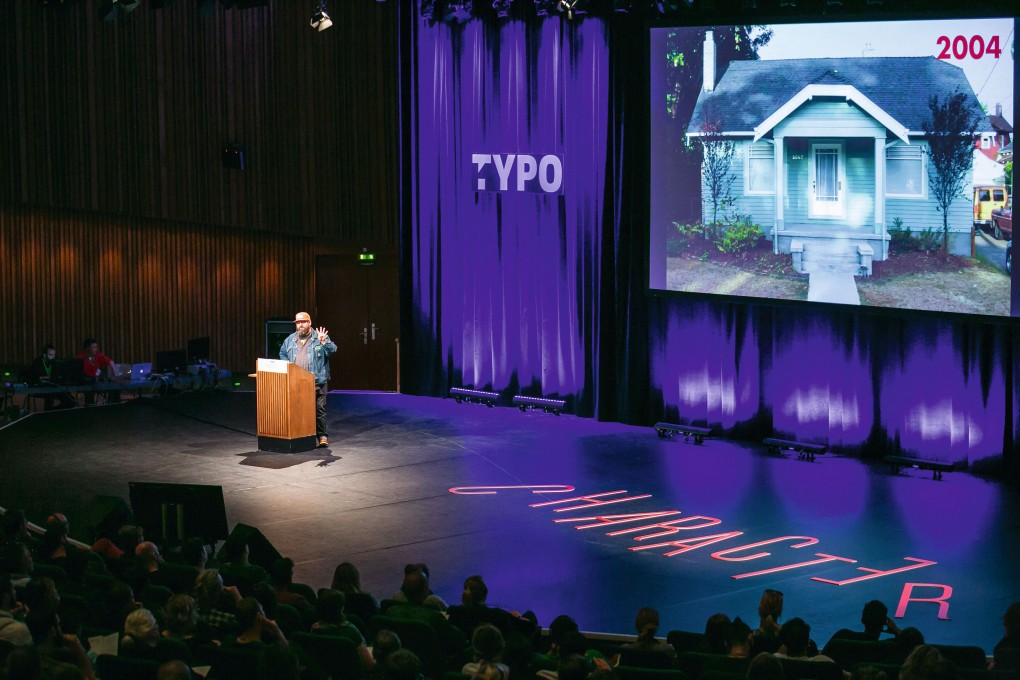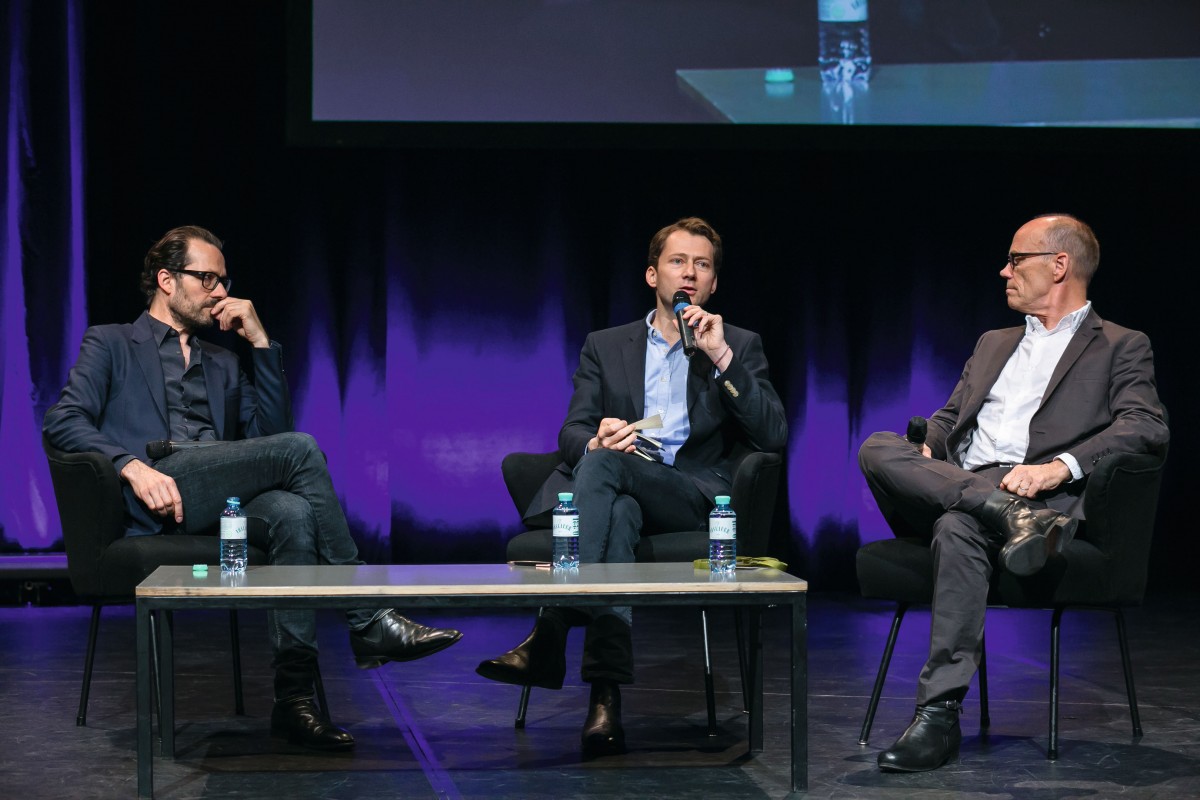
2015 타이포 베를린 : 3 days of Typo Berlin
베를린의 연례 타이포 컨퍼런스 ‘타이포 베를린’은 올해 세계문화의 집(Haus de Kulturen der Welt)에서 진행되었다. 디자인 연설자들의 정수에 해당하는 3일의 강연을 듣기 위해 다양한 분야의 창작자들이 먼 곳에서부터 이곳을 찾았다.
타이포 베를린 2015
Day.1
타이포의 첫 번째 연설자는 철학자이자 문화 이론가 존 소와(Jon Sowa)였다. 그는 현대 디자인 뒤에 숨겨진 전위적인 가치관에 관한 깊은 탐구를 하며 참가자들과의 대화에 불을 붙였다. 사회 세계를 해방적인 방향으로 발전시키려는 움직임과 세계 자본주의에 적응하라고 강요하는 시장 사이 이어지는 갈등에 대해서도 이야기했다. 소와는 창작자들에게 이를 ‘현대 예술적인 창작물의 가장 중요한 특징’으로 인정하길 촉구했다.
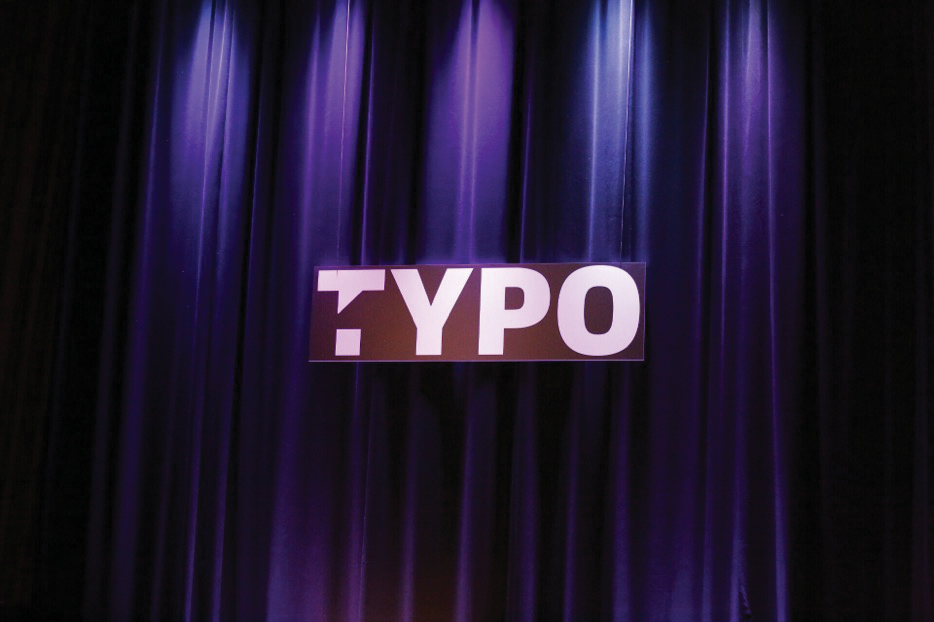
Typo 2015, Berlin
사람들을 휩쓸고 간 이 개관은 프랑스의 장 프랑수아 포르셰(Jean Francois Porchez)의 이야기로 이어졌다. 서체의 개성과, 디자인은 ‘생각의 시각화’라는 조금은 더 미묘한 주제의 강연이었다. 포르셰는 동시에 이러한 이야기도 했다. “좋은 디자인은 보이지 않는 디자인이다. 눈에 보이지 않는 것을 어떻게 만들어야 하나?” 그는 자신이 파리의 버스 전광판을 위해 만든 저해상도 LED 서체를 언급하며, 서체의 아이덴티티를 만드는 것은 구성이라는 기술적인 문제와 연관되어 있고 가독성은 절대적으로 내용과 분리될 수 없음을 보여주었다.
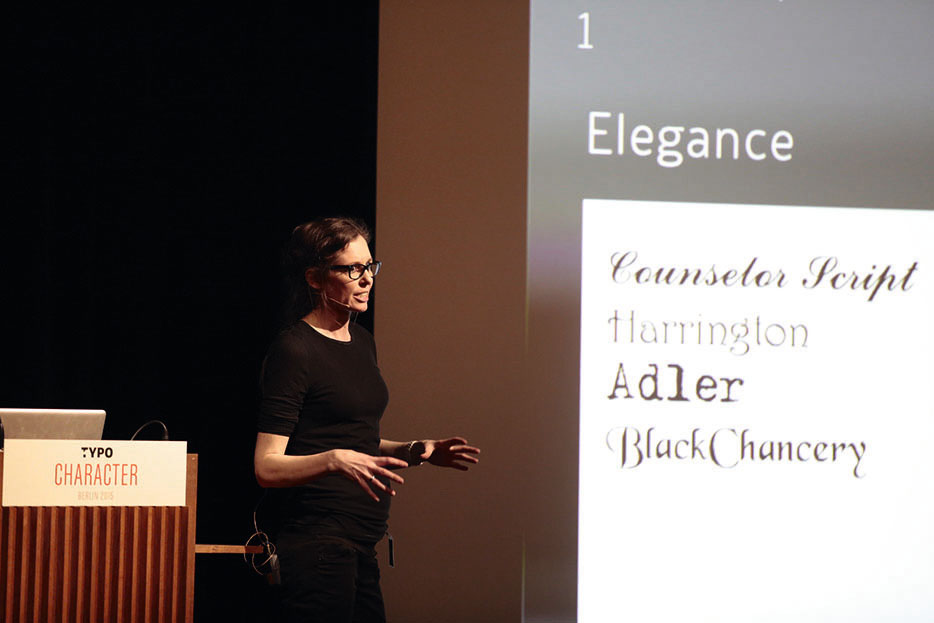
소피 베이르(SOPHIE BEIER) @Typo 2015, Berlin
포르셰의 핵심을 강조하기 위해 나온 듯한 서체 디자이너이자 연구자인 소피 베이르는 서체 해석에 필요한 신경 과학과 심리적 기반에 대해 강연을 진행했다. 내용과 상관없는 형태에 자유자재로 이름을 붙여달라고 청중 일부에게 부탁하기도 했다. 이는 의미론적으로 연결 지으려는 무의식의 역학에 대해 보여주기 위함이었다. 베이르는 이어서 글을 읽기 위해서는 결국 서체의 개성을 무시해야 한다고 이야기했다. 사람 마음이 세세한 부분까지 모두 집중할 수는 없기 때문이다. 결국 “서체는 시선을 끌어당김과 동시에 내용을 전달해야 한다는 충돌을 내재하고 있다”고 결론지었다.
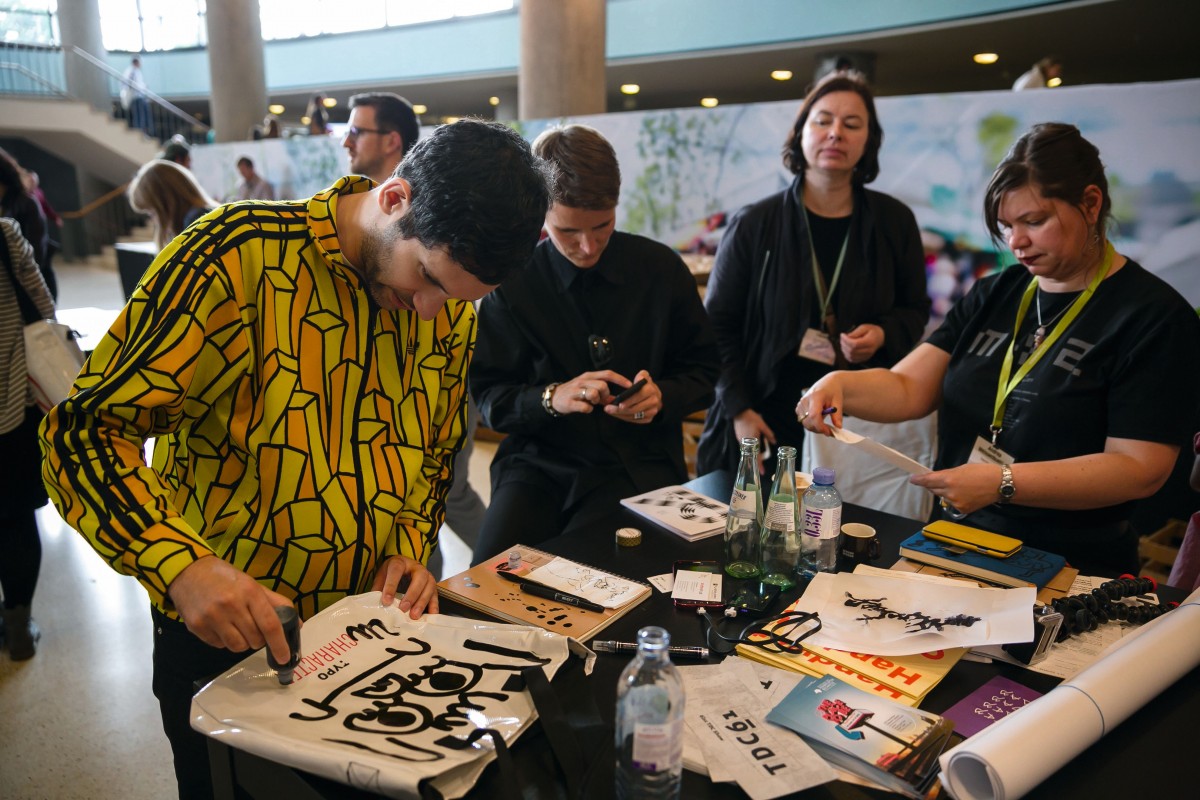
존 버거맨(JOHN BURGERMAN) @Typo 2015, Berlin
첫날부터 과하게 이지적인 내용만 오가고 있다는 생각이 들 때쯤 영국의 일러스트레이터 존 버거맨이 등장했다. 그는 보다 가벼운 접근법을 소개했고 언제 어디서든 마주치는 모든 매체에 그림을 끄적이라고 홀을 가득 채운 사람들에게 이야기했다. 실패에 관한 생각은 버리라는 말도 덧붙이면서 말이다. 버거맨은 축구 경기에 한 족제비가 갑작스럽게 침범한 텔레비전 방송 영상을 보여주었다. 그는 청중들에게 창의적인 작업을 하면서 생기는 갑작스러운 일들을 포용하라고 전했다. ‘일상 작업 속의 족제비를 격려하라’는 것이었다.
타이포 둘째 날은 인사이트와 재미, 두 마리 토끼를 다 잡은 날이었다. 스위스 디자이너 위르그 레니(Jürg Lehni)의 재치 있는 연설이 그 시작이었는데 그는 기계 제작과 로봇 아이덴티티의 탄생에 대해 이야기했다. 레니는 기술을 소비자들을 표준화된 환경에 구속하기 위한 기업의 수단이 아니라 하나의 열린 구조로 바라보길 바랐다. 또한 그는 청중들에게 ‘가족’을 소개했다. 그 ‘가족’은 헥터(Hector)라는 휴대용 스프레이 페인트 기기와 그림을 위한 리타(Rita)라는 녹음, 재생 기기였다. 레니의 강연에서 가장 중요한 키워드는 ‘재미’였다. 그는 자신의 기계 중 몇 가지에 대해서는 본인도 혼란을 느낀다고 이야기하며 자신의 ‘프랑켄슈타인적인 순간’이라고 설명했다.
이후에는 다시 서체의 미래에 대한 이야기로 돌아왔다. 디자이너 피터 발락(Peter Bil’ak)은 OS X를 위해 만들어진 새로운 폰트스탠드(Fontstand)에 대해 흥미로운 이야기를 펼쳐 보였다. 이 어플은 디자이너들이 무료로 폰트를 테스트해보고 원래 가격의 극히 일부만 지불하며 한 달씩 빌려 쓰는 시스템을 제공한다. “파티 초대장을 위해 폰트를 단 한 번 사용하든 전 세계적인 마케팅 캠페인을 위해 10년 동안 사용하든 사용자는 같은 가격을 내야 하잖아요.” 그는 폰트스탠드가 이러한 서체 라이선스의 가장 큰 문제에 대한 해결책이 될 수 있을 것이라 이야기했다.
타이포의 셋째 날에도 사람들의 의욕은 수그러들 줄 몰랐다. 쾌활한 선동가 애런 제임스 드레이플린은 디자인을 통해 ‘아니요’보다 ‘예’라고 대답하는 게 왜 더 가치 있는지 설명했다. 또 친구들을 위해 작업하다 보니 미국의 대통령을 위한 디자인도 하게 되었다는 이야기도 내놓았다.
타이포의 든든한 조력자 에릭 슈피커만은 산업 디자이너 콘스탄틴 그리치치와 함께 무대에 올라 활자의 의미에 대해 토론했다. 그리치치는 규모가 작은 클라이언트의 작업을 의뢰받으며 디자인에 급진적으로 접근할 수 있었다고 이야기했다.
혼란이 디자인에 미치는 영향에 대해 논한 에릭 케셀스의 유쾌한 강연은 큰 호응을 불러일으켰고, 동시에 자칭 ‘세계 최악의 호텔’을 위한 성공적인 광고 캠페인을 알리는 역할도 했다. 마지막으로 일러스트레이터 크리스토프 니만(Christoph Niemann)이 디지털 시대 속 디자인을 위한 도전과 기회에 대해 솔직한 이야기를 털어놓으며 올해의 타이포 컨퍼런스를 마무리 지었다.